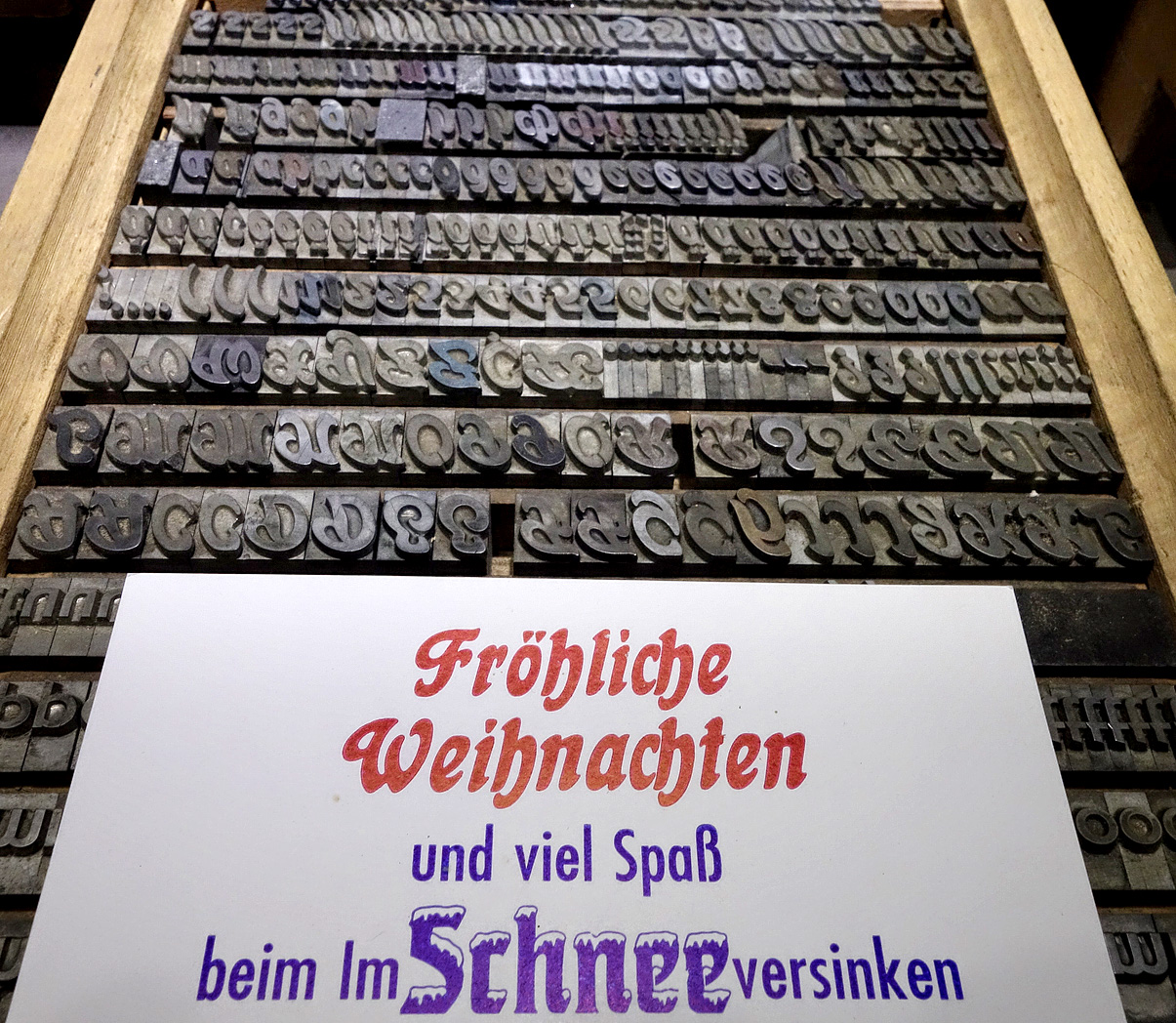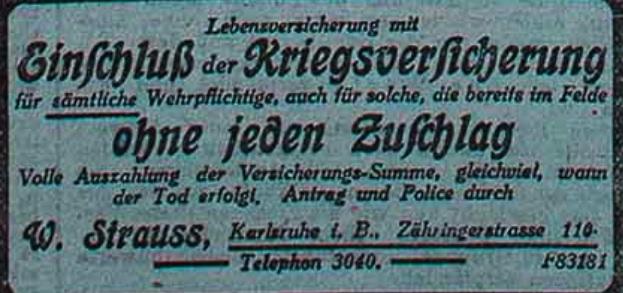
Frankfurter Zeitung 1916
Einschluß, Kriegsversicherung, ohne jeden Zuschlag, …
Das muss eine Schrift einer kleineren Gießerei sein, im Seemann habe ich sie jedenfalls nicht unter den Akzidenz-Kursivschriften finfen können (weir entfernt ähnliches, ja, aber eben nicht diese.
Eine Chance auf eine digitale Version? Eher nicht
Die Belvedere stand in der Bauerschen Hauptprobe von 1907, der Seemann (1926, S. 226) gibt als Erscheinungsjahr 1906 an. Ich habe ein wenig davon, leider ohne B. Die gedruckte Karte ist eine Schülerarbeit.3167.jpg